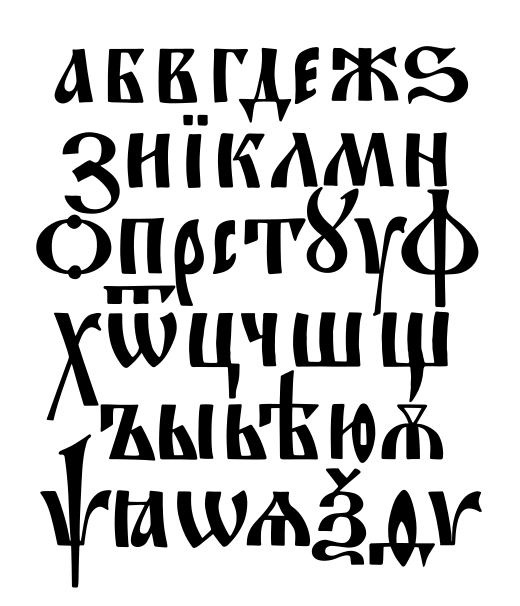
Греческий (византийский) алфавит
Алфавит византийских греков лёг в основу других православных азбук: славянских (не только
кириллицы, но и сильно видоизменённой глаголицы),
коптской, готской и двух албанских.
Имеет коды (& # + 913-937 + 😉 для заглавных букв и 945-969 для строчных:
Α α Β β Γ γ Δ δ Ε ε Ζ ζ
Η η Θ θ Ι ι Κ κ Λ λ Μ μ
Ν ν Ξ ξ Ο ο Π π Ρ ρ Σ σ (ς)
Τ τ Υ υ Φ φ Χ χ Ψ ψ Ω ω.
Также может обозначаться мнемонически от «&» + «Alpha» + «;» до «&» + «omega» + «;»:
Α α Β β Γ γ Δ δ
Ε ε Ζ ζ Η η Θ θ
Ι ι Κ κ Λ λ Μ μ Ν ν Ξ ξ
Ο ο Π π Ρ ρ Σ σ Τ τ
Υ υ Φ φ Χ χ Ψ ψ Ω ω.
- Греческие шрифты. С надстрочными знаками и без надстрочных знаков.
Коптский алфавит
Греческий алфавит стал обслуживать фонетику
афразийского языка [возврат к истокам].
Насколько удачно? Может быть на основе коптского составить новые алфавиты для
О коптском языке смотрите страницу «Египетская языковая ветвь».
- Коптский Алфавит
Готский алфавит
Готы говорили на языке восточно-германской группы. Продвинувашись из Прибалтики в Причерноморье, они подошли к границам Византии. Были и врагами её, и союзниками, и защитниками и наёмниками. Из Византии же и приняли христианство — поэтому письмо переняли от греков.
Старославянская кириллица
Подробную информацию о происхождении кириллицы и ее связи с глаголицей смотрите на странице Славянские письменности.
Албанские алфавиты (греческо-кириллические)
Среди тех европейских систем письма, который ведут свою историю от греческого алфавита,
письменности средневековой Албании кажутся наиболее странными.
Впервые существование одного из албанских алфавитов было обнаружено в 1850 г.
в небольшом городке Эльбасан на юге Албании.
Судя по всему, этот «эльбасанский» алфавит был изобретен не ранее второй половины 18 века.
Еще один (курсивный) вариант албанского письма приписывается авторству некоего Бутакукье и датируется 1840 годом. В самой Албании существовали и другие точки зрения — предполагали, что местные алфавиты зародились здесь еще в средневековье. Однако некоторые факты, и прежде всего форма знаков письма, говорит об обратном: скорее всего, они являются позднейшими модификациями и стилизациями греческого алфавита с небольшим влиянием кириллицы. Причем некоторые буквы напрямую заимствованы из сербского варианта кириллического письма. На сегодняшний день оба алфавита вышли из употребления — это произошло после того, как в 1908 году Албанский конгресс в г. Монастир провозгласил, что единственным шрифтом для албанского языка станет латинский алфавит.
Удивительно следующее:
1) получается, что албанцы до своей исламизации были православными, а не католиками;
2) мусульманизация была тотальной и христиан-албанцев не осталось;
3) албанцы отказались от мусульманского арабского письма (как турки). |
Эльбасанский алфавит
Албанский курсивный алфавит Бютакукье
«Сантии даков» — зачаровывающая подделка?
Как этрусское или латинское письмо перенимали соседи этрусков и римлян,
первое время не внося в алфавит никаких изменений,
так и греческая азбука служила письменной системой народов, взаимодействующих с древними эллинами,
в её полном и неизменном виде, как, например, у фригийцев.
История обнаружения пластин, вкратце, такова.
В конце 19 века в Румынии были обнаружены т.н. Дакские сантии — золотые пластины с древними письменами общим числом около 400.
Король Кароль I, решил переплавить часть пластин, и на вырученные от продажи золота средства построить дворец.
К счастью, перед тем как расплавить пластины, он приказал сделать их точную копию на свинце.
- Сантии даков: доступ запрещён. Автор-любитель относится к сторонникам подлинности дакийских сантий, однако собрал, возможно, полную коллекцию фотографий «золотых пластин даков».
- Сантии Даков — Золотая книга фракийцев. Пример одной из бредовых расшифровок. Но зато на таблицы можно посмотреть.